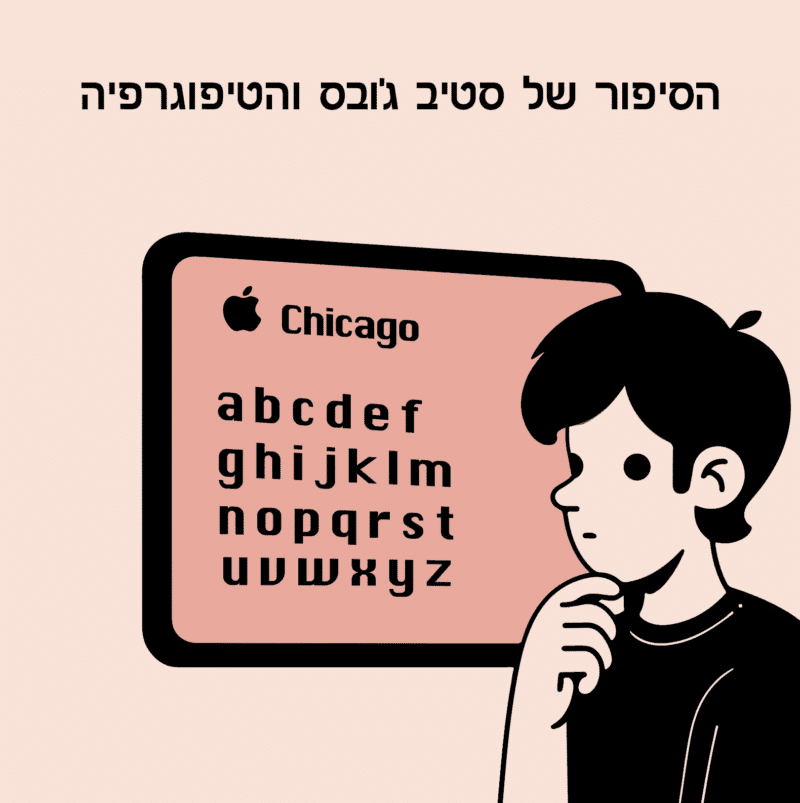
סטיב ג'ובס, אחד המייסדים המבריקים של אפל, תמיד ידע לראות מעבר למה שנראה לעין. הסיפור של ג'ובס עם טיפוגרפיה התחיל בשנות ה-70, כשהוא היה סטודנט צעיר באוניברסיטת ריד.
באותם ימים, ג'ובס היה תלמיד ללא כיוון ברור. הוא החליט לפרוש מהלימודים לאחר שישה חודשים בלבד, אך נשאר בקמפוס כדי ללמוד בקורסים שהעניינו אותו. אחד מהקורסים הללו היה קורס קליגרפיה.
הקורס הזה, שנראה בתחילה כחסר תועלת, היה נקודת מפנה בחייו של ג'ובס. הוא נחשף לראשונה ליופי והאלגנטיות של עיצוב האותיות, לפרופורציות המדויקות ולמרווחים בין האותיות שהופכים טקסט ליצירת אמנות. הוא למד על גופנים סריפיים וסנס-סריפיים ועל השפעתם על הקריאה והאסתטיקה.
כשג'ובס הקים את אפל מספר שנים לאחר מכן, הוא לא שכח את השיעורים שלמד בקורס הקליגרפיה. כאשר הם פיתחו את המקינטוש הראשון, הוא דאג שהמחשב יכלול יכולת תצוגה של גופנים מגוונים ואיכותיים – משהו שלא היה קיים במחשבים אחרים באותה תקופה.
המקינטוש היה המחשב הראשון שהציע מבחר גופנים יפים ומעוצבים היטב, עם ממשק משתמש גרפי שאפשר בחירה נוחה בגופנים. זה היה מהלך מהפכני שהשפיע על כל תעשיית המחשוב והעיצוב.
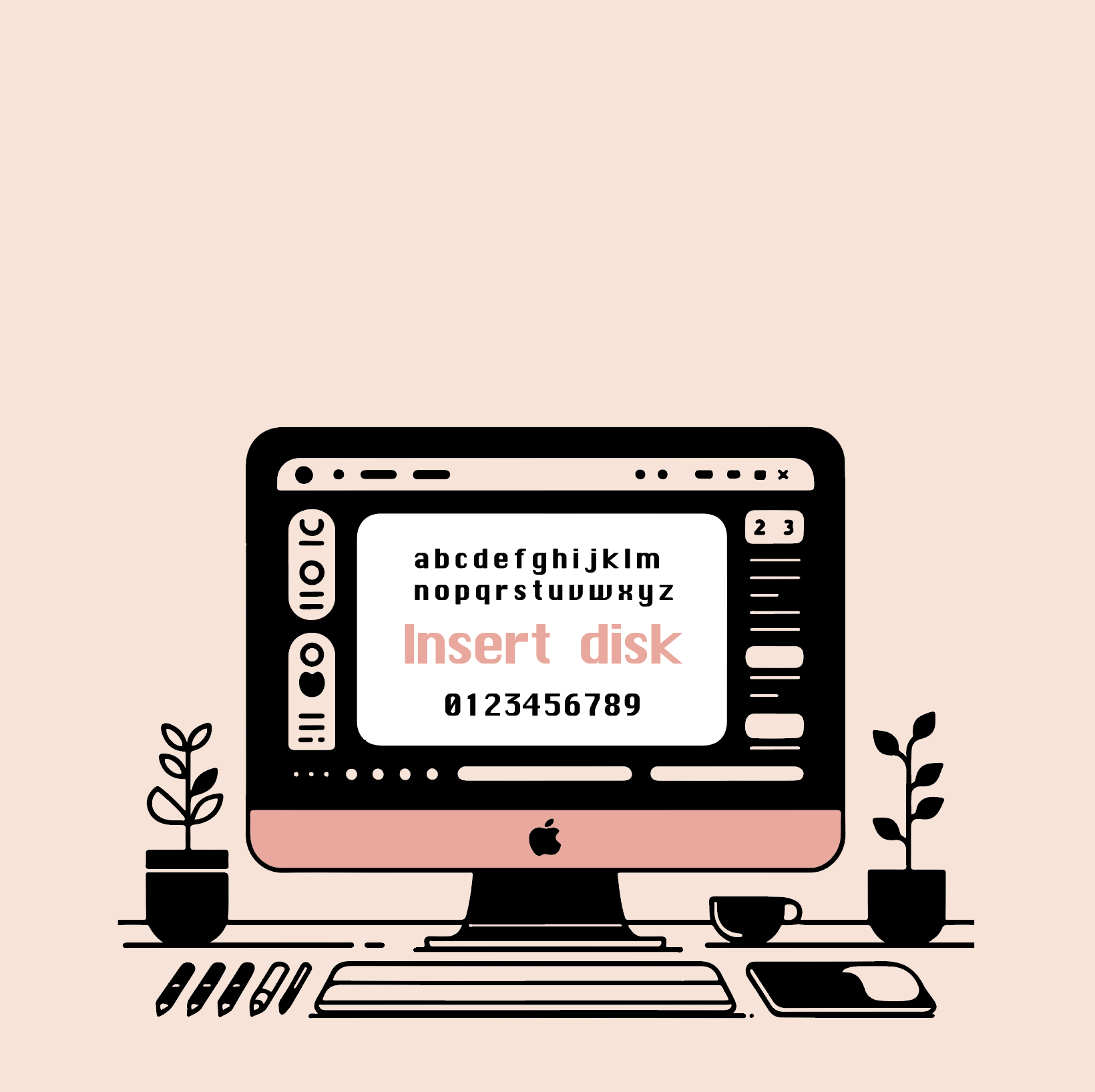
הסיפור של סטיב ג'ובס והטיפוגרפיה הוא דוגמה מצוינת לאיך תחום שנראה שולי וחסר חשיבות יכול להפוך למרכיב מרכזי במוצר שמשנה את העולם. בזכות האהבה של ג'ובס ליופי ולעיצוב, כולנו נהנים מחוויית קריאה ועיצוב טובה יותר במכשירים הדיגיטליים שלנו.